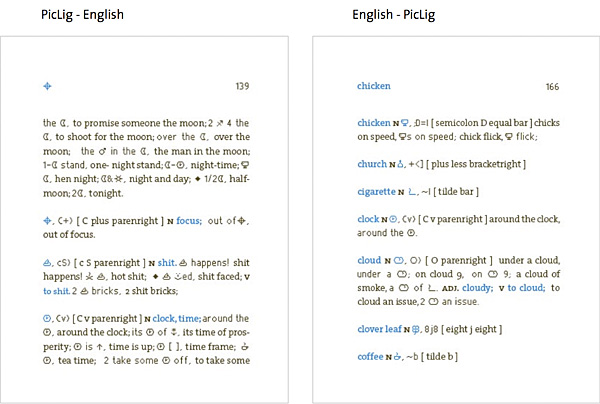
Neue FF PicLig: eine Schrift zum LiebhabenPicLig steht für Picture Ligatures, also
Ligaturbilder. PicLig, entworfen von Christina Schultz, ist eine
»intelligente« Pixelschrift, eine kuriose Mischung aus
SMS-Ästhetik und OpenType-Technik. Werden Buchstaben in einer bestimmten
Reihenfolge getippt, verwandeln sich diese durch die OT-Ligaturautomatik in
Symbole. Auf diese Art serviert PicLig kurze, sympathische Botschaften aus
![]() Die Buchstabenbilderschrift FF PicLig muss man einfach
lieben:
![]() Grüße zum Geburtstag mal anders geschrieben, und anders gelesen: ![]() Während sich bei typografischen Ligaturen einzelne Buchstaben zu Kombinationsbuchstaben verbinden (zum Beispiel fi zu fi), erzeugt FF PicLig keine Schriftzeichen sondern Piktogramme. ![]() PicLig ist eine Schrift, die ohne Opentype nur schwer zu bedienen wäre. Sie nutzt die Ligatur-Funktion, mit der man einer definierte Zeichenkette ein einzelnes Zeichen zuordnen kann ... im Fall von PicLig ist das ein exakt zugewiesenes Symbol. Den gängigen Symbole wie mail, sun, female, male usw. konnte ein Unicodewert zugeordnet werden; andere Symbole tragen einen unverwechselbaren Namen – wie z. B. flower, dog – und haben keinen Unicodewert. Der Wortschatz von PicLig besteht aus Buchstaben, Zahlen und den 112 essenziellen Symbolen. Sie wurden nicht nach ästhetischen Kriterien ausgewählt, sondern nach Nützlichkeit. Inspirationsquelle waren die Piktogramme der öffentlichen Gebäude, der Wegweisung und der emotionalen Befindlichkeit der digitalen Kommunikation. Menschen kommunizieren gerne mit Text und Symbolen, was nicht zuletzt die Emoticon-Kultur beweist, die in den USA inzwischen die animierte 3-D-Phase erreicht hat. Gefühle lassen sich mit einem kleinen Symbol oft besser zeigen, als mit dem geschriebenen Wort. Oder eine harte Textbotschaft lässt sich durch ein Augenzwinkern ;-) relativieren. ![]() Wie bei der gesprochenen Sprache schätzen die Menschen die individuelle Tonalität, eine angenehme Betonung. Warum soll das bei der geschriebenen Sprache anders sein? PicLig kommt diesem Bedürfnis entgegen: mit einer neuen Ästhetik, Überraschungsmomenten und täglich neu zu entdeckenden Piktogrammen. Kommunikation passiert schnell und auf kleinstem Raum, siehe SMS. Wie schön, wenn man ein Wort oder gleich mehrere Wörter durch ein sympathisches Herz ersetzen kann. Und durch die Verwendung aussagekräftiger Bilder wird man überall verstanden. Tatsächlich hilft PicLig da weiter, wo man eine Fremdsprache nur sehr schlecht versteht. Das nachfolgende Beispiel wendet sich an jene Freunde der französischen Sprache, die in der Schule nicht aufgepasst haben und jetzt in Paris verliebt sind: ![]() Eine tragende Idee hinter PicLig: Piktogramme mit Hilfe von Buchstaben-Eselsbrücken bauen. Die OpenType-Technik übernimmt den Rest: ![]() Die PicLig-Entwerferin Christina Schultz wird demnächst auf einer eigens eingerichteten Seite www.piclig.net zur Schrift ein Wörterbuch veröffentlichen. Fontblog wird darüber berichten. ![]() Ein Online-Wörterbuch zur PicLig ist schon fast fertig ... ![]() Doppelseite aus dem Piclig-Wörterbuch Leider ist das Probesetzen von PicLig auf der technisch nicht mehr aktuellen FontShop-Seite nur mit den alphabetischen Zeichen möglich: der auf OpenType basierte Austausch von Buchstabenketten zu einem Symbol funktioniert dort nicht. Die Animationen oben auf dieser Seite vermitteln ein gutes Gefühl der Funktionsweise in OpenType-fähigen Programmen. Herausgegeben: Di - November 22, 2005 at 11:38 vorm. | |